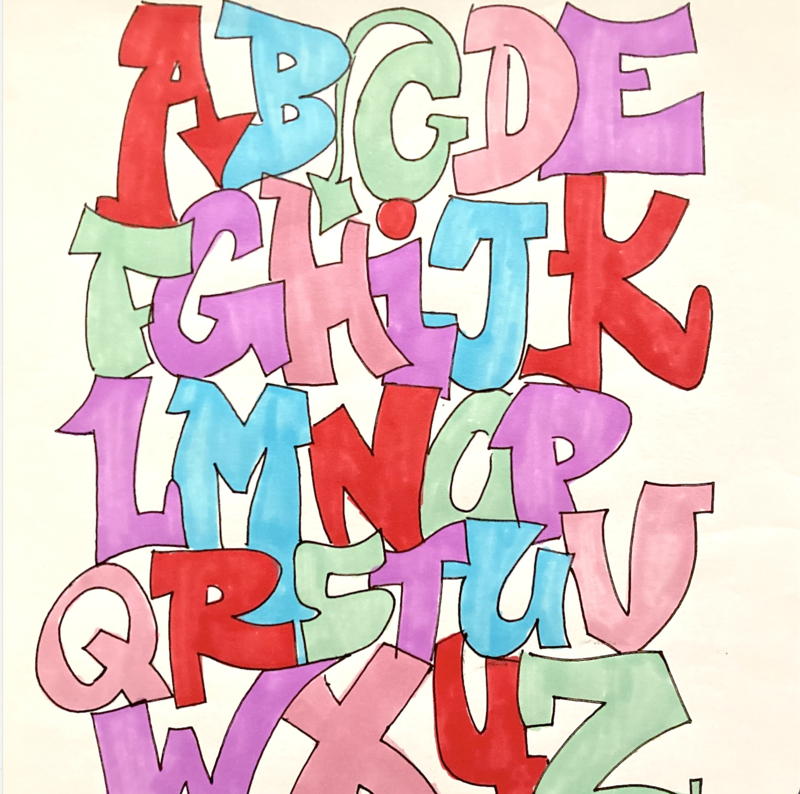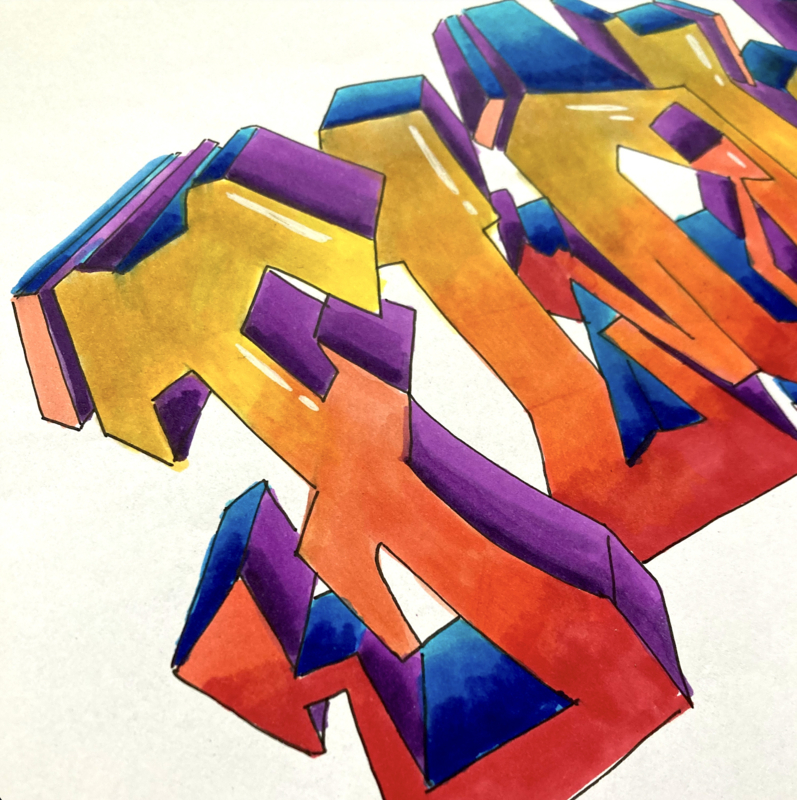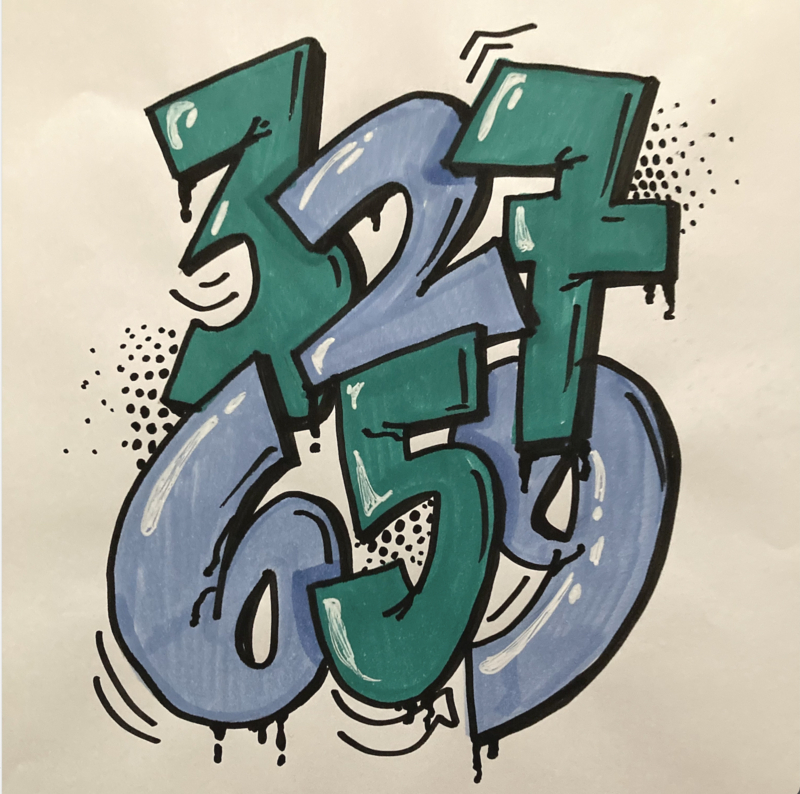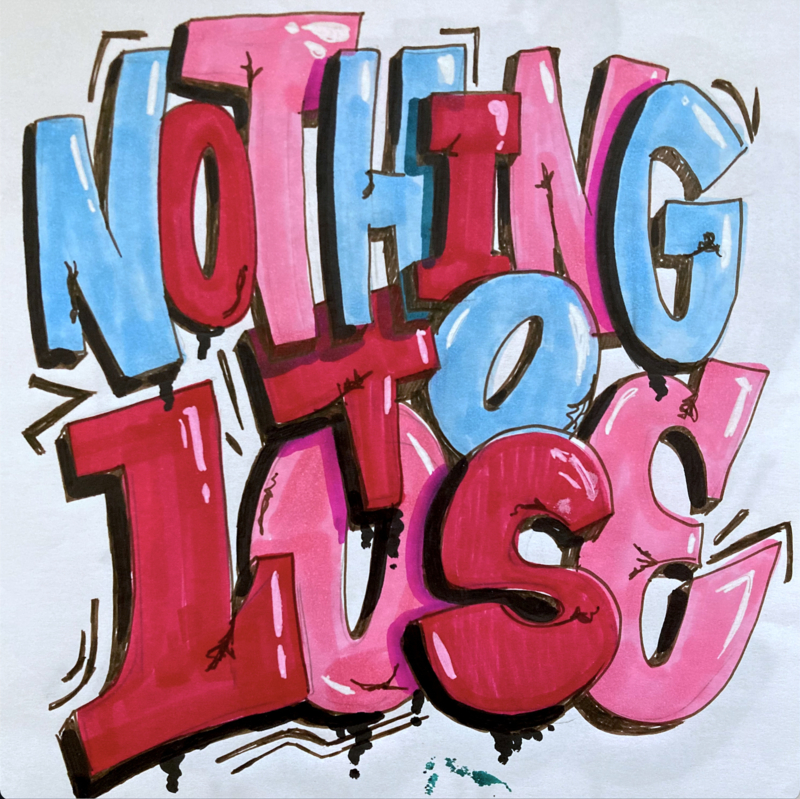
WORKSHOP 'PIECE MAKEN MET GRAFFITI LETTERS' (12-18 jaar)
Maak met een woord je eigen graffiti piece met markers op papier!
In deze workshop leer ik je hoe je verschillende graffiti letters kunt tekenen. Een prima basis om -als je ermee verder gaat- je eigen stijl gaat vinden. Een eigen stijl is er belangrijk in de graffiti scene. Je gaat beginnen met twee verschillende soorten letters, die je al een eigen stijl kunt geven natuurlijk. Hoe bouw je een letter op. Welke elementen vind je tof om te gebruiken? Pijlen, druipende lijnen, bewegingslijnen, er is zoveel mogelijk. Je gaat je 'letter piece' in een achtergrond zetten. Van schets naar een piece. Als je helemaal tevreden bent ga de de piece inkleuren met markers, felle kleuren doen het altijd goed in een piece! Mocht er tijd zijn dan kan ik je ook nog iets uitleggen over het blenden van kleuren. En als bonus gaan we nog een persoonlijke tag maken, die je gelijk kunt gebruiken om je net-gemaakte-piece te kunnen ondertekenen.